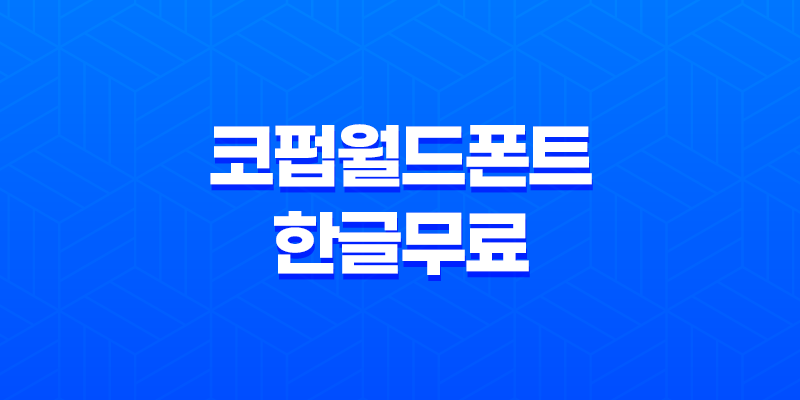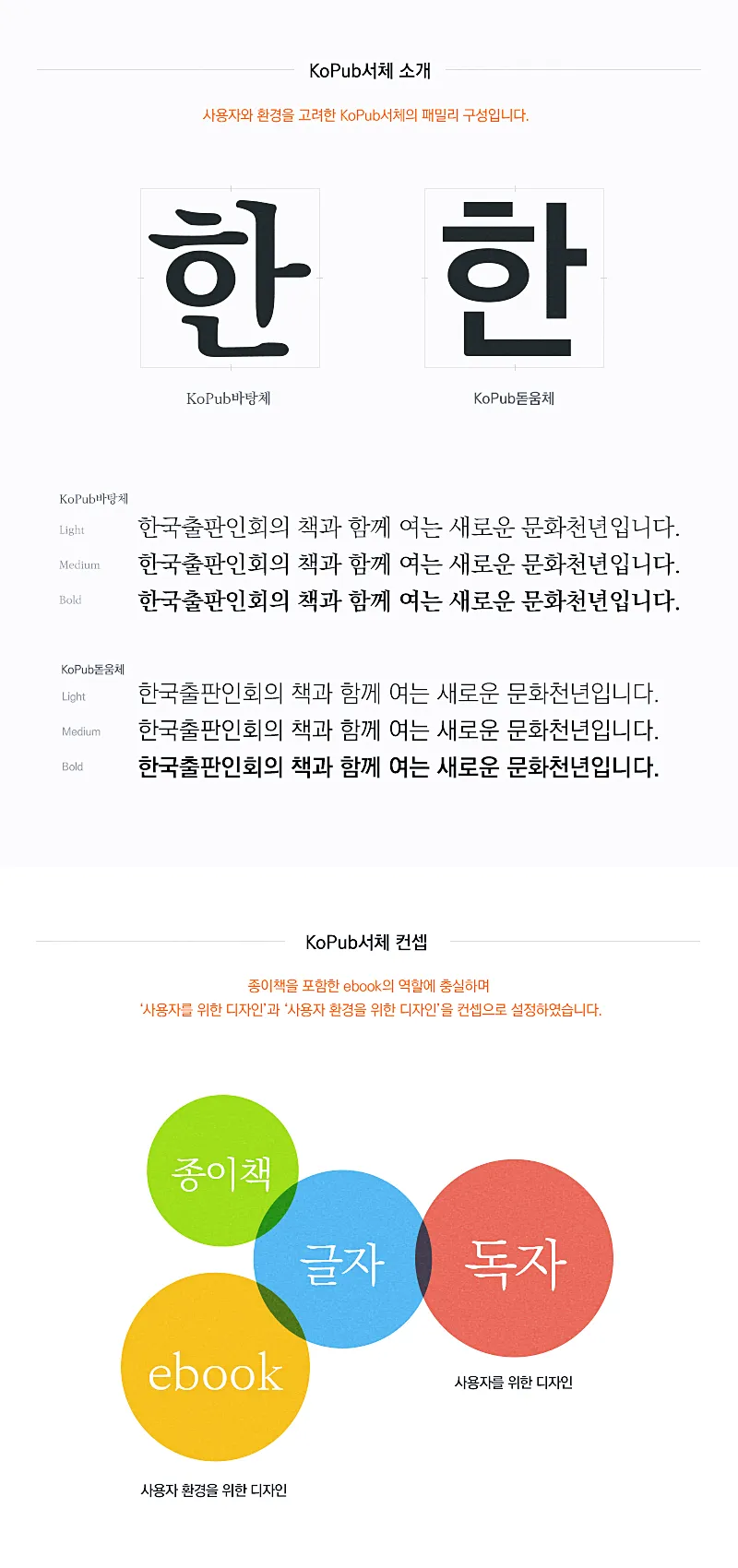
코펍월드폰트 특징과 매력
한글무료 상업폰트 중에서 빈번히 활용되는 폰트로서, 바로 KoPub 폰트라고 불리는데, 이 폰트는 출판 및 교육과 깊은 관련이 있는 곳에서 탄생한 것으로 알려져 있습니다. 그 중에서도 최근에 등장한 코펍월드폰트는 그 어느 때보다도 현대한글과 다양한 언어를 아우르며 디자인 작업에 적합한 폰트로 주목받고 있습니다.
코펍월드폰트의 혁신적인 개선
과거에는 코펍 2.0(KoPub 2.0)이라는 이전 버전만 존재했습니다. 그러나 최신 코펍월드폰트는 기존 버전 대비 혁신적인 발전을 이루어, 고딕체와 바탕체(명조체)로 세분화되었습니다. 이 폰트는 옛한글과 확장 한자, 일본어, 라틴어, 러시아, 히브리어, 아라비아어, 산스크리트어 등 다양한 언어를 지원하여 다국어 디자인 작업에 탁월한 성능을 발휘합니다.
다양한 글자와 웨이트의 매력
코펍월드폰트는 현대한글 11,172자, 옛한글 9,170자, 영문 94자, KS한자 4,888자, 확장한자 1,390자 등 다양한 글자와 3가지의 웨이트(굵기)를 보유하고 있습니다. 이는 사용자가 원하는 스타일에 따라 선택할 수 있도록 다양성을 제공하는 것입니다.
코펍 돋움체 디자이너들의 최애
코펍 돋움체(KoPub 돋움체)는 다국어를 제외한 디자이너들 사이에서 가장 인기 있는 폰트 중 하나입니다. 이 폰트는 가독성과 심미성을 동시에 살려 ebook환경에서 빛을 발하고 있습니다. 가독성이 탁월한 이 폰트는 전자출판뿐만 아니라 다양한 디자인 작업에 활용되고 있습니다.
지원 받는 언어와 다양한 글자 수
이 폰트는 다국어를 지원하며, 산스크리트어 128자, 일본어 189자, 라틴 확장 784자, 키릴 문자 304자, 아랍어 255자, 히브리어 143자 등 다양한 언어와 문자를 포함하고 있습니다. 이는 사용자가 언어의 제약 없이 다양한 프로젝트에 적용할 수 있음을 의미합니다.
코펍월드폰트와 코펍 돋움체는 각자의 특징을 살려 다양한 디자인 환경에서 빛을 발하고 있습니다. 가독성이 우수한 이 두 폰트를 활용하여 프로젝트를 진행한다면, 사용자들은 더욱 풍부한 경험을 누릴 것입니다. 최신 디자인 트렌드에 발맞춰, 코펍월드폰트와 코펍 돋움체를 적극 활용하여 창의적이고 독창적인 작업을 만들어보세요.